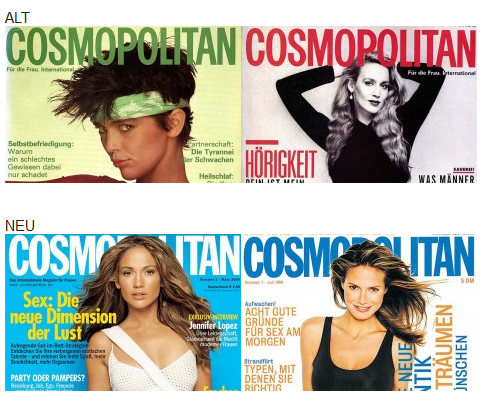
Alte Cosmopolitan-Schrift gesucht!
Ich bin auf der Suche nach der ganz alten Cosmopolitan-Schrift vom Cover. Weiß jemand was das für eine Schriftart sein könnte?
Ich weiß, dass die heutige Schrift eine Franklin Gothic Extra Condensed ist vielleicht hilft das ja weiter :(
ich wage mal die behauptung, dass die buchstaben des alten schriftzugs nicht direkt aus einer (digital) existierenden satzschrift entnommen sind. die cosmopolitan ist ja auch nicht gerade eine unbekannte hinterhofzeitschrift. insofern kann es gut sein, dass die wortmarke seinerzeit – im stil einer amerikanischen grotesk – von grund auf gezeichnet wurde. mit heutigen, digitalen schriften kommst du da höchstens in die nähe. drei vorschläge:
https://www.myfonts.com/fonts/urw/neo-franklin/d-light/?meta=/32386/COSMOPOLITAN/Neo+Franklin+D+Light
https://www.myfonts.com/fonts/shinn/brown/extra-bold-condensed/?meta=/82913/COSMOPOLITAN/Brown+ExtraBold+Condensed
https://www.myfonts.com/fonts/fontbureau/benton-sans/extra-comp-medium/?meta=/126706/COSMOPOLITAN/Benton+Sans+ExtraComp+Medium